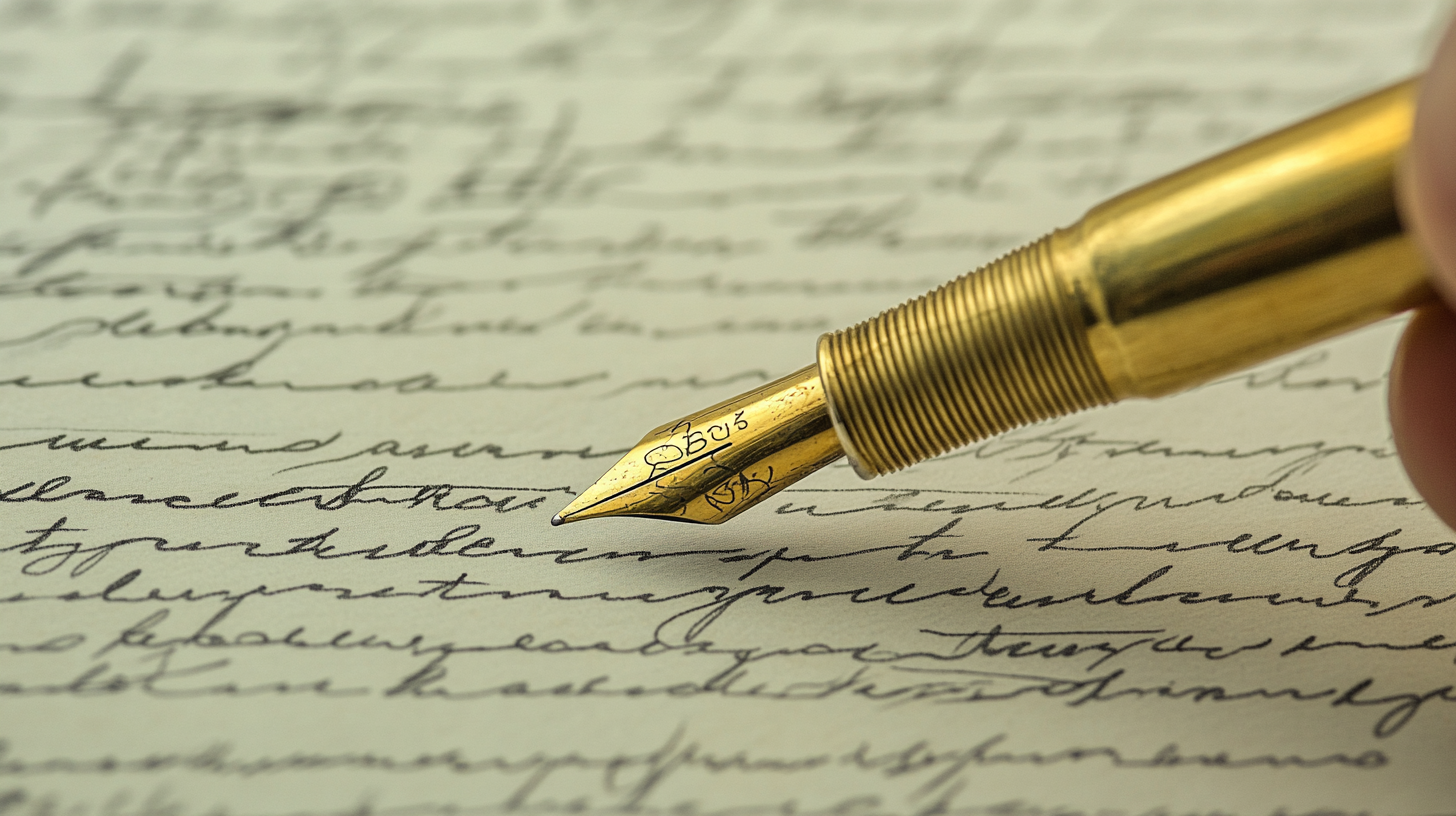
✍ 글씨체는 단순한 글자가 아니라 그 사람의 인상을 좌우하기도 해요. 특히 이력서, 메모, 필기 노트 등에서 깔끔한 글씨는 신뢰감과 전문성을 함께 전달할 수 있답니다. 그래서 많은 분들이 "나도 글씨 예쁘게 쓰고 싶다"는 바람을 가지고 있어요.
하지만 어릴 적 배운 습관이 굳어져서 쉽게 바뀌지 않는 게 현실이죠. 그래서 오늘은 ‘글씨체 바꾸는 법’을 누구나 따라할 수 있도록 실사 비교와 함께 자세히 소개해볼게요. 실제로 변화가 있었던 사례를 통해 동기부여도 함께 드릴게요! 😊
✍ 글씨체 교정이 필요한 이유
글씨체가 마음에 들지 않는다고 느낀 적 있으신가요? 많은 사람들이 손글씨에 대해 스트레스를 받아요. 이유는 단순해요. 알아보기 힘든 글씨는 보는 사람뿐 아니라 본인에게도 불편을 주기 때문이에요.
특히 학생들이 필기할 때 글씨가 엉망이면 복습할 때 불편함이 커요. 직장인의 경우 회의록이나 메모를 공유할 때도 글씨체가 주는 인상이 꽤 크답니다. 반듯하고 정리된 글씨는 그 사람의 성격과 태도를 그대로 반영한다고 보는 시선도 있어요.
그래서 글씨체 교정은 단순히 ‘예쁜 글씨’를 넘어서, ‘자기 표현’과 ‘대외적인 이미지 관리’에 중요한 역할을 해요. 누군가는 글씨만 봐도 성격을 짐작한다고 하잖아요? 그만큼 영향력이 커요.
예를 들어 한 취업준비생이 자소서에 손글씨로 간단한 메모를 남겼는데, 그 글씨가 너무 깔끔해서 면접관이 호감을 느꼈다고 해요. 이처럼 사소한 글씨체가 인생의 터닝포인트가 되기도 하죠.
📊 교정 전과 후 차이 요약표
항목 교정 전 교정 후 가독성 낮음 매우 높음 자신감 부족함 향상됨 주변 반응 무관심 또는 지적 칭찬 및 긍정적 반응 활용도 낮음 높음 내가 생각했을 때, 글씨체는 '자기관리의 시작'이라고 믿어요. 타인에게 신뢰를 줄 수 있는 첫 걸음이기도 하고요. 글씨를 고친다고 해서 모든 게 변하는 건 아니지만, 글씨를 통해 보여지는 나의 모습은 분명 달라진답니다! 💫
📝 글씨체 바꾸는 실질적 방법
글씨체를 바꾸는 방법은 생각보다 체계적이에요. 막연히 '예쁘게 써야지'라고 생각하기보다는, 구체적인 계획과 단계가 필요하답니다. 먼저 자신의 현재 글씨를 찍어서 분석해보는 게 시작이에요. 어떤 부분이 삐뚤한지, 자간은 넓은지, 높낮이는 일정한지를 체크해야 해요.
그다음은 교정할 글씨체를 선택하는 단계예요. 기본 바탕체, 궁서체, 교과서체 등 다양한 글씨체 중에서 자신이 목표로 삼을 스타일을 정해야 해요. 요즘은 유튜브나 인스타그램에도 예쁜 손글씨 체본이 정말 많아요. 거기서 따라 쓰기 좋은 모델을 정하고 프린트해서 따라 써보는 게 효과적이에요.
이후에는 반복적인 ‘베껴쓰기’ 훈련이 필요해요. 하루에 30분, 꾸준히 같은 글씨체를 따라 쓰다 보면 자연스럽게 손에 익게 돼요. 중요한 건 힘을 빼고 가볍게 쓰는 습관을 들이는 거예요. 처음에는 속도를 줄이고, 천천히 정자체를 쓰는 연습을 반복해보세요.
또 하나 꿀팁은 '세로쓰기' 훈련이에요. 가로쓰기보다 세로쓰기가 획 정리에 도움이 많이 돼요. 세로줄 노트를 활용해서 중심선을 기준 삼아 연습하면 정돈된 느낌의 글씨를 익히기 좋아요. 이런 작은 방법들이 모여 나만의 글씨체를 만들어준답니다.
🖋 글씨체 교정 단계별 요약
단계 내용 1단계 현재 글씨 분석 및 진단 2단계 교정할 목표 글씨체 선정 3단계 반복적인 베껴쓰기 훈련 4단계 세로쓰기 및 속도 조절 연습 5단계 일상에서 실전 적용해보기 이 단계들을 2주 이상 꾸준히 실천하면 글씨체에 확실한 변화가 생겨요. 특히 자음과 모음을 일정한 간격으로 정렬하는 습관이 생기면, 훨씬 더 단정한 느낌을 줄 수 있어요. 글씨체를 교정한다는 건 단순한 취미가 아니라 자존감 회복에도 큰 도움이 된답니다! 🌱
📖 꾸준한 연습 방법 공개
글씨체 교정에서 가장 중요한 건 바로 '꾸준함'이에요. 아무리 좋은 도구나 방법을 알아도 꾸준히 하지 않으면 변화는 생기지 않아요. 하루 10분이라도 '글씨 쓰는 시간'을 정해두고 반복하는 게 가장 핵심이에요.
우선 추천하는 연습 방법은 '기본 획 반복 연습'이에요. 가로선, 세로선, 대각선, 원 그리기 같은 아주 기본적인 동작을 종이에 반복하는 거예요. 이걸 매일 3~5분만 해도 손 근육의 움직임이 달라진답니다.
그다음은 '짧은 문장 필사'예요. 명언, 책 구절, 일기 속 문장을 그대로 옮겨 적으면서 정자체 훈련을 해보세요. 단, 속도를 줄이고 정확성에 집중하는 게 포인트예요. 글자 간격과 줄 정렬을 신경 쓰며 써야 해요.
또한 '내 글씨체 분석 노트'를 만드는 것도 좋아요. 매일 쓴 글을 찍어서 저장하거나 붙여 놓고 스스로 비교하면서 피드백을 주는 거죠. 그렇게 한 달만 기록해 보면, 놀라운 변화가 보일 거예요. 사진으로 남기면 더 실감 나고 동기부여도 돼요!
📅 추천 연습 루틴
요일 연습 내용 소요 시간 월요일 기본 획 반복 (세로/가로/원) 10분 화요일 명언 필사 + 자간 체크 15분 수요일 세로쓰기 + 줄 간격 훈련 10분 목요일 자기 이름 30회 쓰기 5분 금요일 글자 구성 요소 분리 연습 15분 이 루틴을 따르면 빠르면 2주, 보통 한 달 내에 눈에 띄는 변화가 생겨요. 특히 하루라도 빠지지 않고 실천했을 때, 손글씨가 훨씬 안정적으로 바뀐 걸 직접 느끼게 될 거예요. 꾸준함이 글씨체 교정의 진짜 열쇠랍니다! 🔐
📸 교정 전·후 실사 비교
눈으로 직접 보는 변화만큼 동기부여가 되는 건 없죠! 이번엔 실제 교정 과정을 거친 분들의 손글씨 실사 사진과 함께, 어떻게 달라졌는지를 구체적으로 비교해 볼 거예요. 이건 단순히 '예쁘다' 수준을 넘어서, 실용성과 자신감을 동시에 얻은 사례들이에요.
첫 번째 사례는 30대 직장인 A씨예요. 원래는 악필로 유명해서 회의록을 아무도 못 읽었대요. 하지만 3주간 글씨체 훈련을 하면서 기본 획 연습과 세로쓰기 훈련을 집중했더니, 지금은 직장 동료들이 따라 쓰고 싶어 할 정도로 예쁜 글씨가 되었어요.
두 번째는 중학생 B양이에요. 교과서 필기체가 너무 삐뚤해서 복습에 어려움을 겪었는데, 필사 앱과 종이 연습장을 병행하면서 자간, 줄 맞춤을 훈련한 결과 학기 말에는 '노트상'까지 받았다고 해요! 변화가 사진에서도 확연히 느껴진답니다.
마지막은 40대 주부 C님 사례예요. 자녀에게 좋은 글씨체를 보여주고 싶어서 교정에 도전했는데, 처음엔 떨리는 손 때문에 힘들어했지만 한 달간 따라 쓰기와 필사로 안정적인 필체를 가지게 되었어요. 지금은 손글씨로 편지를 써서 지인들에게 보내는 게 취미라고 해요 😊
📷 실사 비교 전·후 표
이름 교정 전 교정 후 소요 기간 직장인 A씨 삐뚤빼뚤, 자간 불균형 반듯하고 읽기 쉬운 필체 3주 중학생 B양 줄 안 맞고 크기 불균형 줄 정렬, 크기 통일 4주 주부 C님 불안정한 필체, 획 흔들림 부드럽고 안정적인 글씨 1달 이런 실사 비교를 보면 "나도 한번 해볼까?" 하는 생각이 들죠? 글씨체는 연습하면 누구나 달라질 수 있어요. 꾸준히만 한다면 어떤 글씨라도 훨씬 더 깔끔하고 자신 있는 스타일로 바꿀 수 있답니다. ✨
🙋 실제 사용자 후기
실제로 글씨체를 바꿔본 사람들의 이야기를 보면, 단순한 변화가 아니라 인생의 작은 전환점이 되었다고 해요. 글씨가 예뻐지면 자신감도 올라가고, 주변의 반응도 바뀌면서 자연스럽게 생활 습관까지 좋아지는 경우가 많답니다.
고등학생 정윤이(18)는 “글씨체가 예뻐지고 나서 선생님께 칭찬을 받았어요. 친구들이 노트 빌려달라고 할 정도로 변화가 있었죠. 수업 집중도도 더 좋아졌고요.”라고 말했어요. 글씨체 교정이 학습 습관에도 긍정적인 영향을 줬다는 거죠.
프리랜서 디자이너 윤슬씨(32)는 “원래 낙서처럼 글씨를 써서 클라이언트 앞에서 메모할 때 민망했어요. 그런데 교정하고 나서는 미팅 때에도 자신감 있게 메모할 수 있어서 커뮤니케이션이 훨씬 좋아졌어요.”라고 전했답니다.
또한 육아맘 채은님(38)은 “아이한테 좋은 글씨 보여주고 싶어서 시작했는데, 제가 오히려 힐링 받았어요. 하루에 10분만 조용히 글씨 쓰는 시간이 나만의 힐링 타임이 되었죠.”라며 감정을 나눠줬어요. 손글씨는 마음을 정리해주는 효과도 있죠!
🌟 사용자 만족도 평가표
사용자 만족도 가장 만족한 변화 정윤 (18세, 고등학생) ★★★★★ 수업 집중력 상승 윤슬 (32세, 디자이너) ★★★★☆ 업무 중 자신감 채은 (38세, 주부) ★★★★★ 일상 속 힐링 이처럼 다양한 사람들이 손글씨 교정을 통해 자신만의 이야기를 만들어가고 있어요. 단순히 글씨가 예뻐지는 걸 넘어서 삶의 만족도가 높아지고, 자존감도 회복되는 경험을 하게 되는 거죠. 당신도 오늘부터 시작해보는 건 어때요? ✍
Q3. 교정 효과는 언제쯤부터 나타나나요?
A3. 보통 2~4주 정도 연습하면 눈에 띄는 변화가 생겨요. 개개인 차이는 있지만, 사진으로 기록하면 더욱 잘 느낄 수 있어요.
Q5. 어떤 글씨체부터 연습하는 게 좋을까요?
A5. 교과서체나 바탕체처럼 정형화된 글씨체부터 시작하는 걸 추천해요. 기준이 명확해서 교정이 쉬워요.
Q6. 필사할 문장은 어떻게 고르면 좋을까요?
A6. 좋아하는 책 구절이나 명언이 좋아요. 감정이 담기면 손글씨에도 생기가 돌고 지속하기도 쉬워요!
Q7. 아이와 함께 교정 연습을 해도 될까요?
A7. 너무 좋아요! 부모와 아이가 함께 연습하면 서로 자극도 되고, 재미있게 습관화할 수 있어요.
Q8. 손떨림이 심한데 글씨체 교정이 가능할까요?
A8. 손떨림이 있더라도 천천히, 짧은 획부터 연습하면 충분히 가능해요. 처음엔 어렵지만 안정된 획을 익히면 좋아져요.